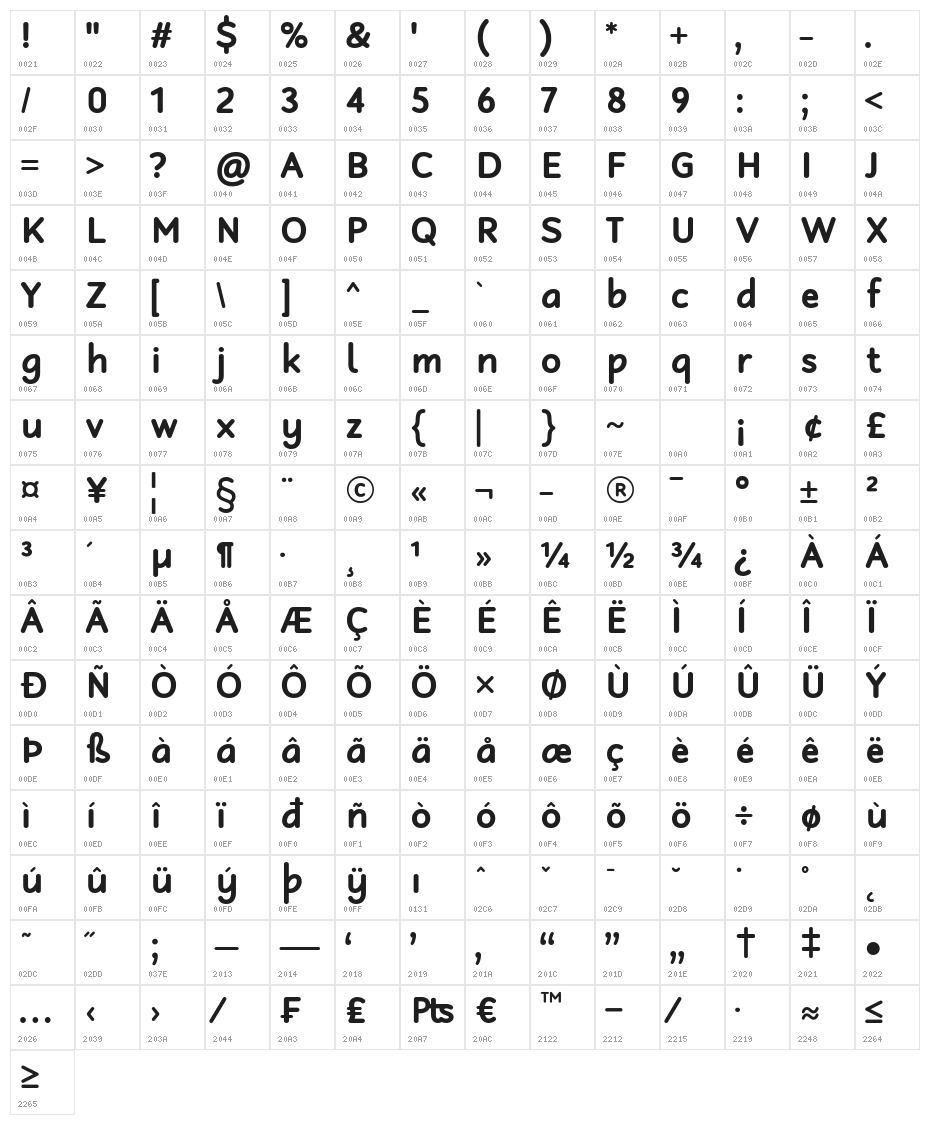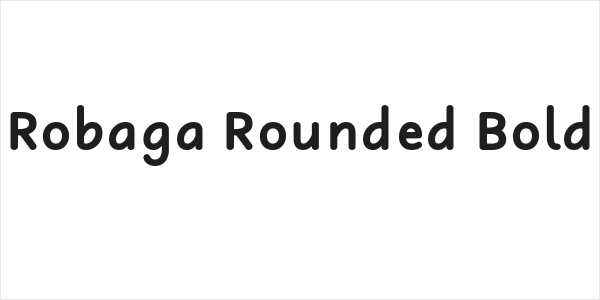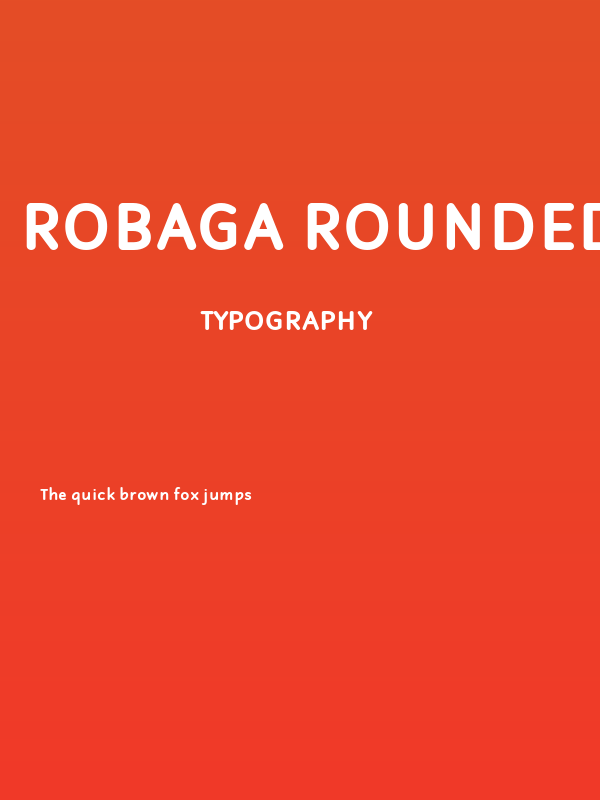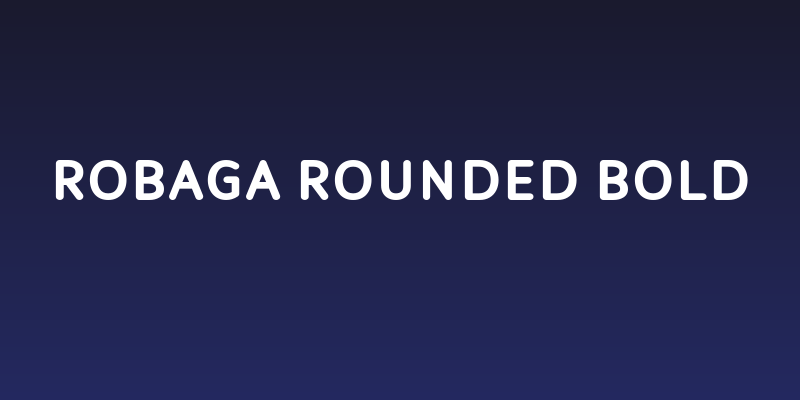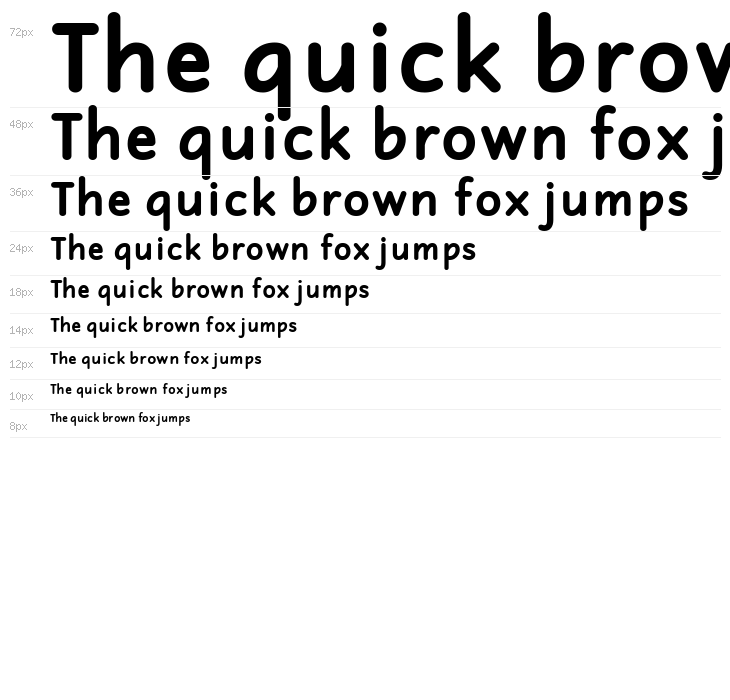
Robaga Rounded Bold Font
| おすすめプロジェクト | Ideal for branding, headlines, posters, and children's books due to its playful and approachable style. |
Robaga Rounded Bold